Es war ein nasskalter Abend im letzten November, als ich an meinem Küchentisch in Bonn saß und auf einen Stapel verschmierter Briefumschläge starrte. Ich wollte nur ein paar Adressen in einer schlichten, sauberen Schrift schreiben. Trotz meines Hintergrunds als Grafikerin sah mein Versuch eines 'einfachen' Monoline-Stils aus wie die Handschrift eines Grundschülers, der es eilig hat. Die Linien wackelten, die Abstände stimmten nicht und die Tinte brauchte auf dem glatten Papier ewig zum Trocknen.
Warum 'einfach' oft die größte Hürde ist
Monoline Lettering klingt erst einmal simpel. Im Gegensatz zum Brush Lettering verzichtet man auf den Wechsel zwischen dünnen Aufstrichen und dicken Abstrichen. Man nutzt eine konstante Linienbreite. Doch genau hier liegt die Falle: Ohne die variierende Strichstärke fällt jeder kleine Wackler sofort auf. Es gibt kein Kaschieren durch schwungvolle Schatten. In der Typografie ist die Gleichmäßigkeit alles.
Anfang des Jahres begann ich, meine Fortschritte systematisch in einer Tabelle zu erfassen. Ich wollte wissen, warum meine Linien nicht so ruhig wirkten wie die in den Vorlagen. Es stellte sich heraus, dass das Problem oft beim Material beginnt. Viele Anfänger greifen zu extrem glattem Papier, was für Brush Pens toll ist, aber einen Fineliner fast unkontrollierbar macht. Ich habe festgestellt, dass eine 120g/m² Satinierung zwar gut für die Haltbarkeit der Stiftspitzen ist, man aber eine ruhige Hand erst einmal trainieren muss.
Die Suche nach dem System: Sketchnotes oder Lettering?
Im frühen Frühjahr suchte ich nach einem Kurs, der Monoline nicht nur als Randnotiz behandelt. Es gibt zwei Richtungen: Die einen nutzen Monoline für funktionale Notizen, die anderen für ästhetisches Design. Ich habe mir den Sketchnotes Kurs angesehen, der hervorragend ist, wenn man in Meetings schnell Visualisierungen erstellen will. Wer jedoch wissen will, wie man die 26 Buchstaben des lateinischen Alphabets wirklich präzise konstruiert, braucht einen anderen Fokus.
Ich entschied mich für den umfassenderen Handlettering Kurs. Obwohl der Name nach Brush Pens klingt, wird dort die Buchstabenanatomie von Grund auf erklärt. Begriffe wie x-Höhe, Oberlängen und Unterlängen sind für Monoline genauso wichtig wie für komplexe Kalligrafie. Wenn man versteht, wo ein 'o' theoretisch dicker werden würde, kann man es auch in einer gleichmäßigen Linie stabiler zeichnen. Mehr zu meinen allgemeinen Erfahrungen findet ihr auch in meinem Artikel über Beste Handlettering Online Kurse: Meine Empfehlungen nach Monaten am Küchentisch.
Der Wendepunkt: Anatomie und der Kugelschreiber-Trick
Hier kommt eine Beobachtung aus meiner wöchentlichen Praxis, die vielleicht gegen die Intuition spricht: Vergesst für die ersten zwei Wochen die teuren Profi-Fineliner in den Größen 0.1mm, 0.3mm oder 0.5mm. Ich habe gemerkt, dass ich Monoline-Lettering viel schneller mit einem ganz normalen, billigen Kugelschreiber gelernt habe. Der Grund ist der mechanische Widerstand. Ein Fineliner gleitet fast ohne Reibung über das Papier. Ein Kugelschreiber hingegen zwingt einen durch den höheren Widerstand dazu, langsamer und bewusster zu steuern.
In einer stillen Küche spät nachts ist das rhythmische 'skritch-skritch' eines 0.3mm Fineliners auf ultra-glattem Papier fast meditativ. Aber am Anfang war dieses Geräusch für mich eher ein Zeichen von Unsicherheit. Erst als ich zum Kugelschreiber griff, wurden meine Ovale wirklich rund. Ich habe mich oft gefragt, ob meine Kollegen in der Bonner Agentur lachen würden, wenn sie wüssten, dass ich vierzig Minuten lang nur den Buchstaben 'o' übe, um den perfekten Anschlusspunkt zu finden.
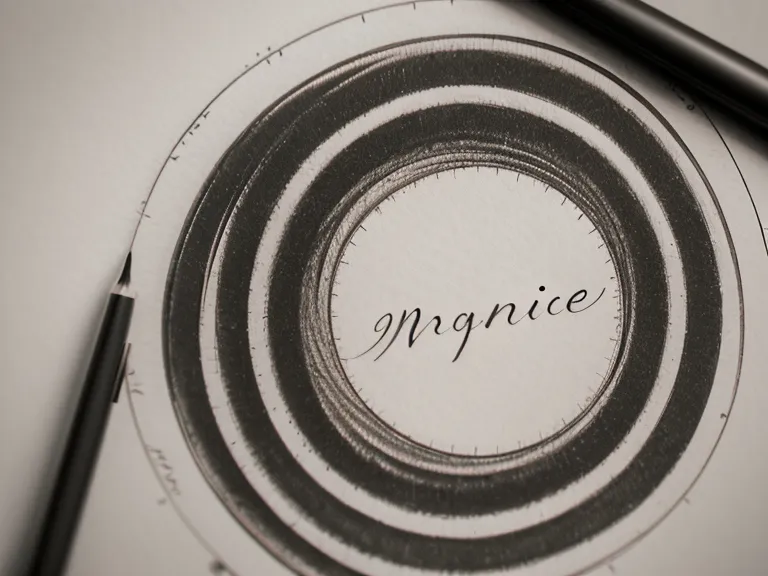
Sechs Wochen am Küchentisch: Wenn es klickt
Nach etwa sechs Wochen täglicher Übung – meistens etwa 30 bis 45 Minuten, bevor ich die Kinder ins Bett bringe oder selbst auf dem Sofa lande – passierte etwas. Die Kontrolle über den Stift war plötzlich da. Ich verstand, wie ich den kleinen Finger als Anker auf dem 120g/m² Papier einsetzen musste, um lange, gerade Linien zu ziehen, ohne dass die Hand verkrampft.
Ein wichtiger Teil dieser Entwicklung war das Modul zur Druckkontrolle im Handlettering Kurs. Auch wenn man beim Monoline keinen Druck ausübt, hilft das Wissen um die Druckpunkte dabei, den Stift gleichmäßiger zu führen. Wer lieber direkt digital startet, sollte sich eher den Digital Lettering Kurs ansehen, da Procreate am iPad ganz eigene Tücken bei der Stabilisierung der Linien hat. Für mich bleibt das Papier am Küchentisch jedoch das ehrlichste Feedback.
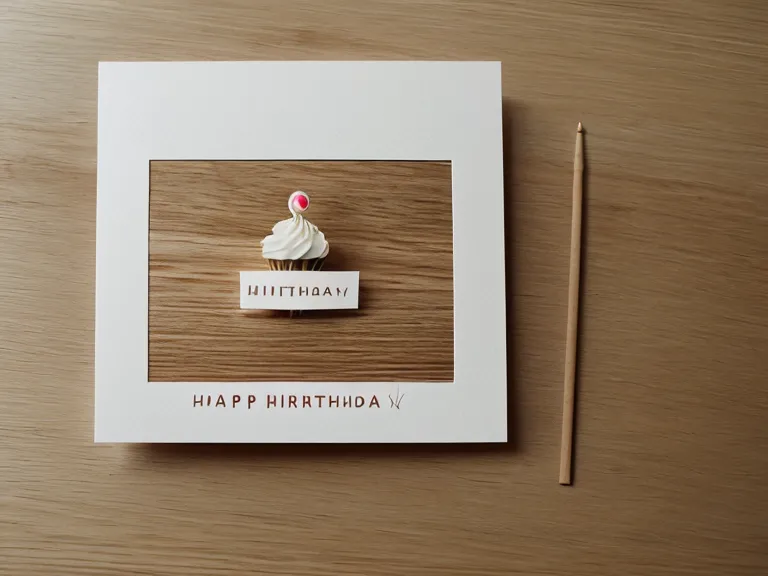
Ein verregneter Sonntag im Juli
An einem regnerischen Sonntagnachmittag im Juli kramte ich die alten Briefumschläge vom November wieder hervor. Der Vergleich war fast erschreckend. Die neuen Entwürfe waren nicht perfekt – ich bin immer noch keine Kalligrafin – aber sie hatten eine Ruhe, die vorher fehlte. Die Buchstabenanatomie stimmte, die Abstände waren gleichmäßig und die Tinte saß genau dort, wo sie hinsollte.
Am Ende ist es wie bei jedem Handwerk: Man muss die Stunden investieren. Wenn ihr bereit seid, ein paar Wochen lang Kringel und Striche zu ziehen, werdet ihr mit einer Schrift belohnt, die endlich so aussieht, wie ihr es euch vorgestellt habt. Wer direkt die Grundlagen der Buchstabenform lernen will, macht mit dem Handlettering Kurs meiner Erfahrung nach den stabilsten ersten Schritt.